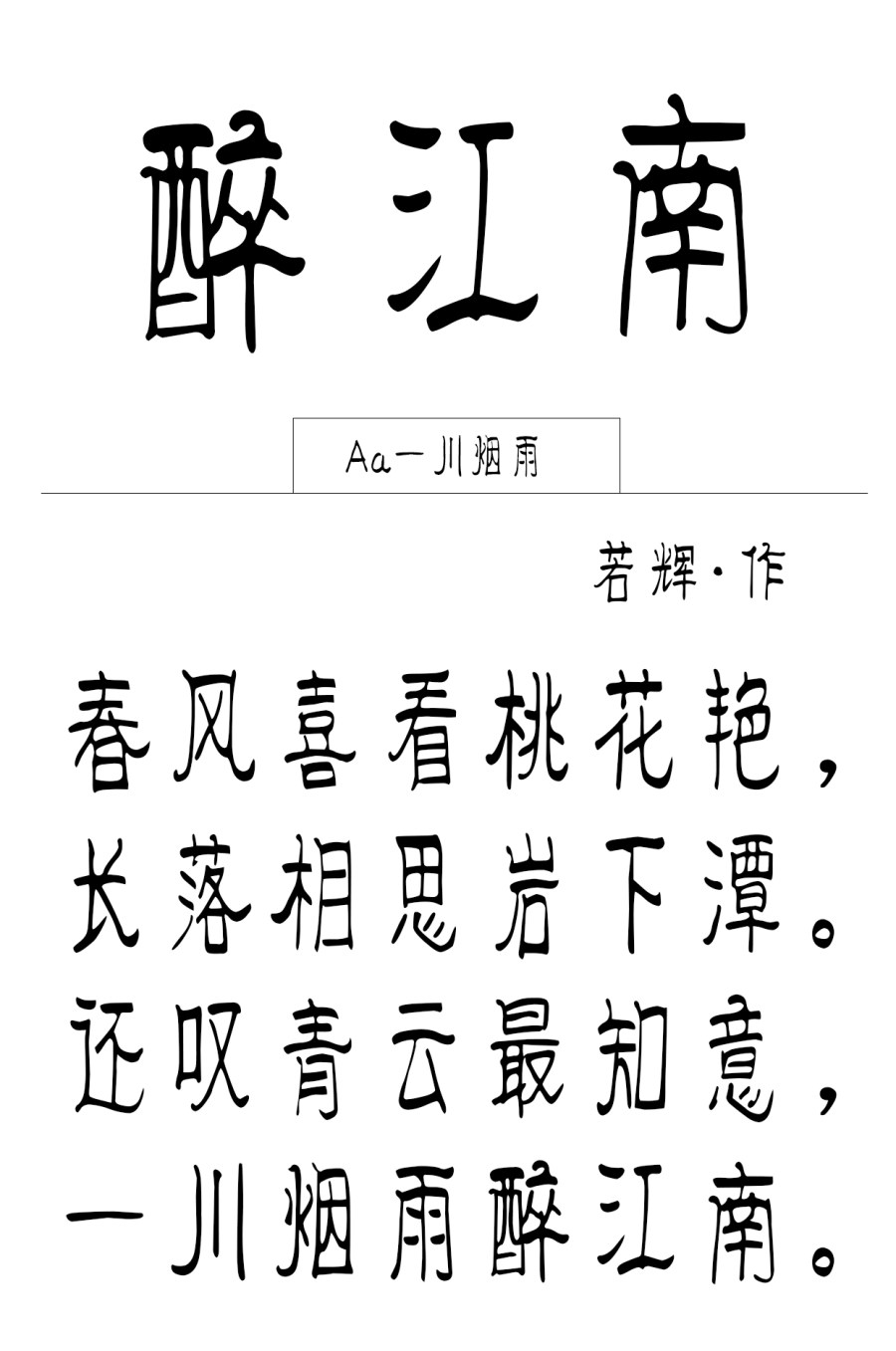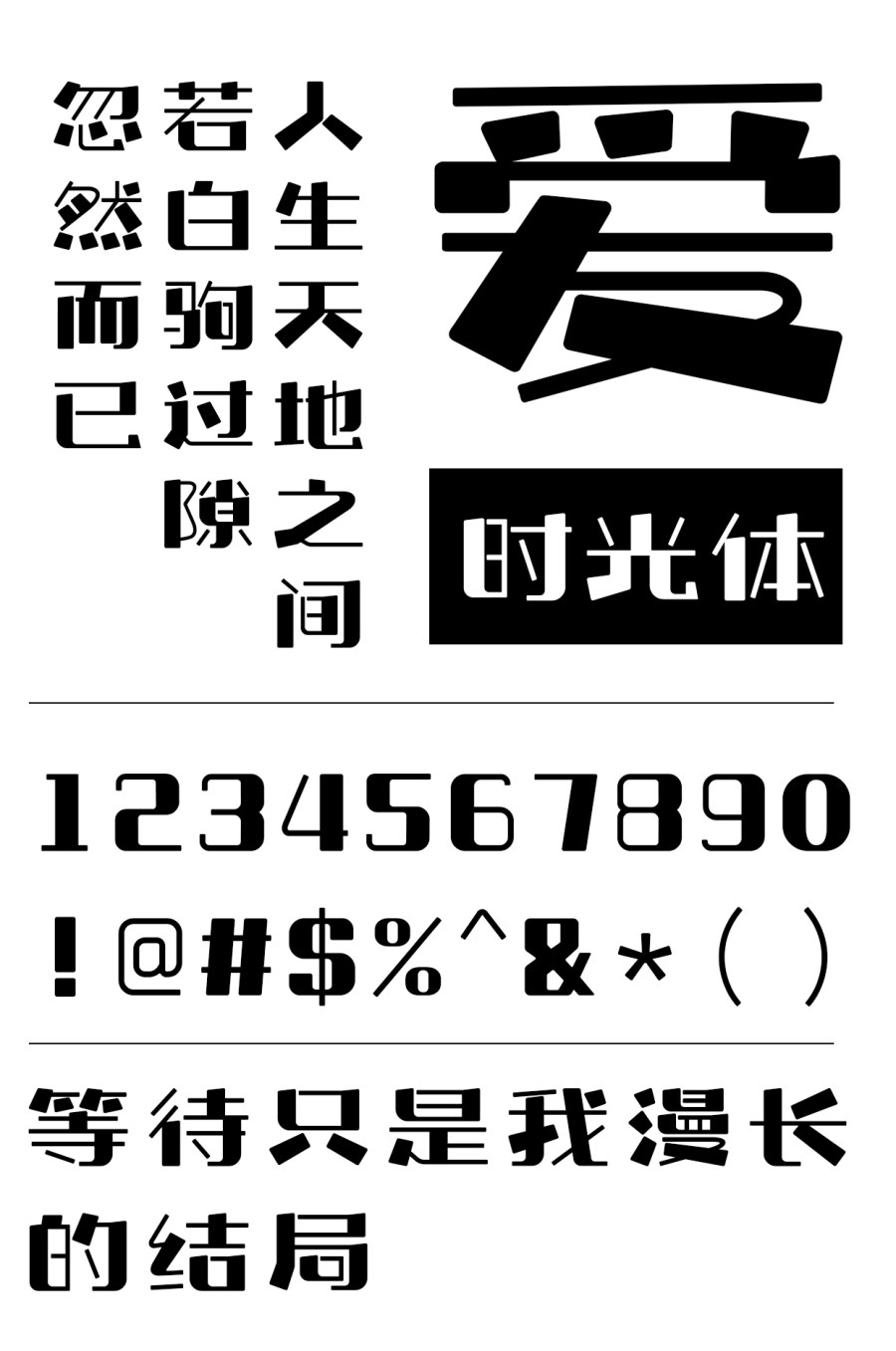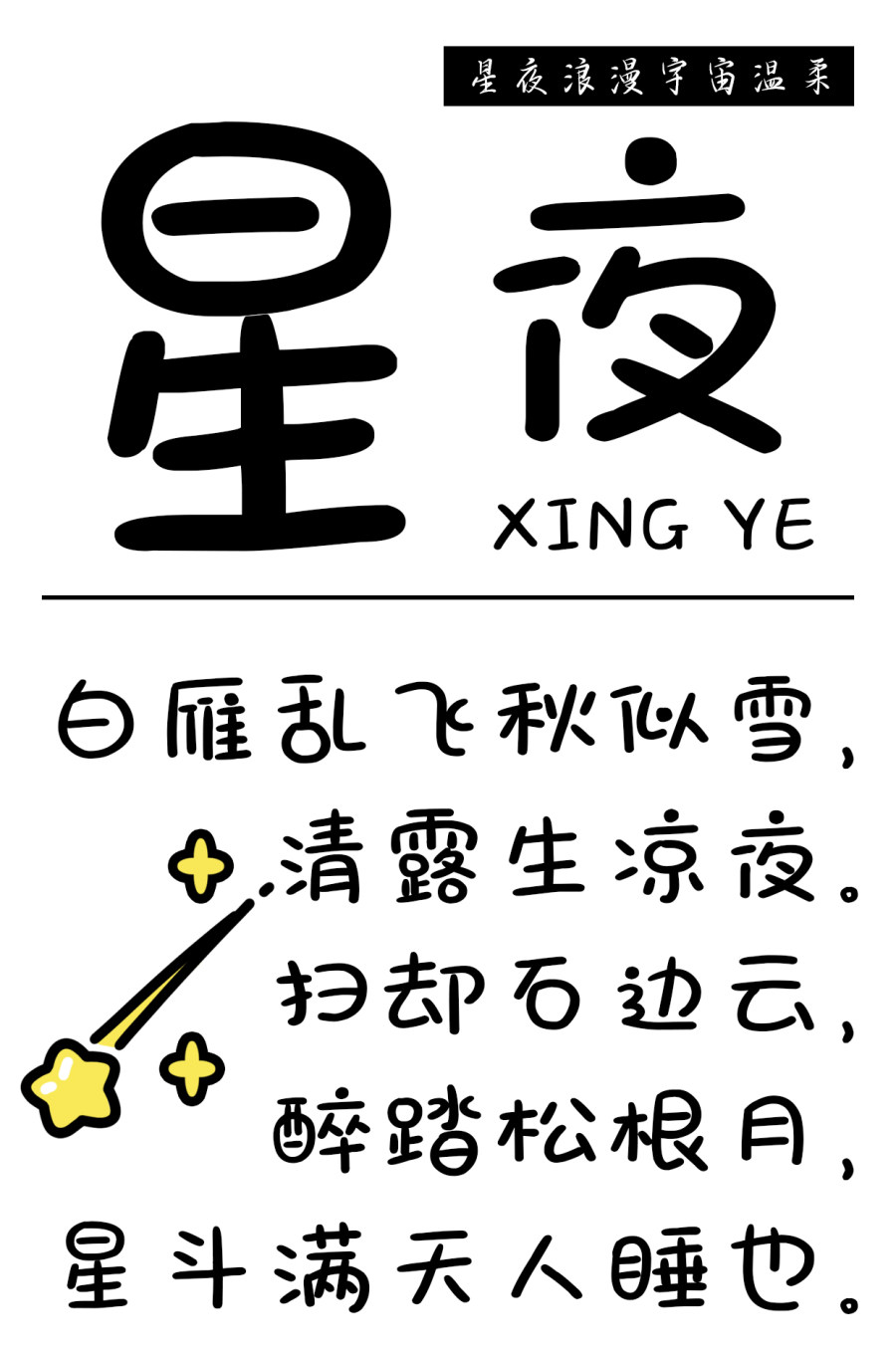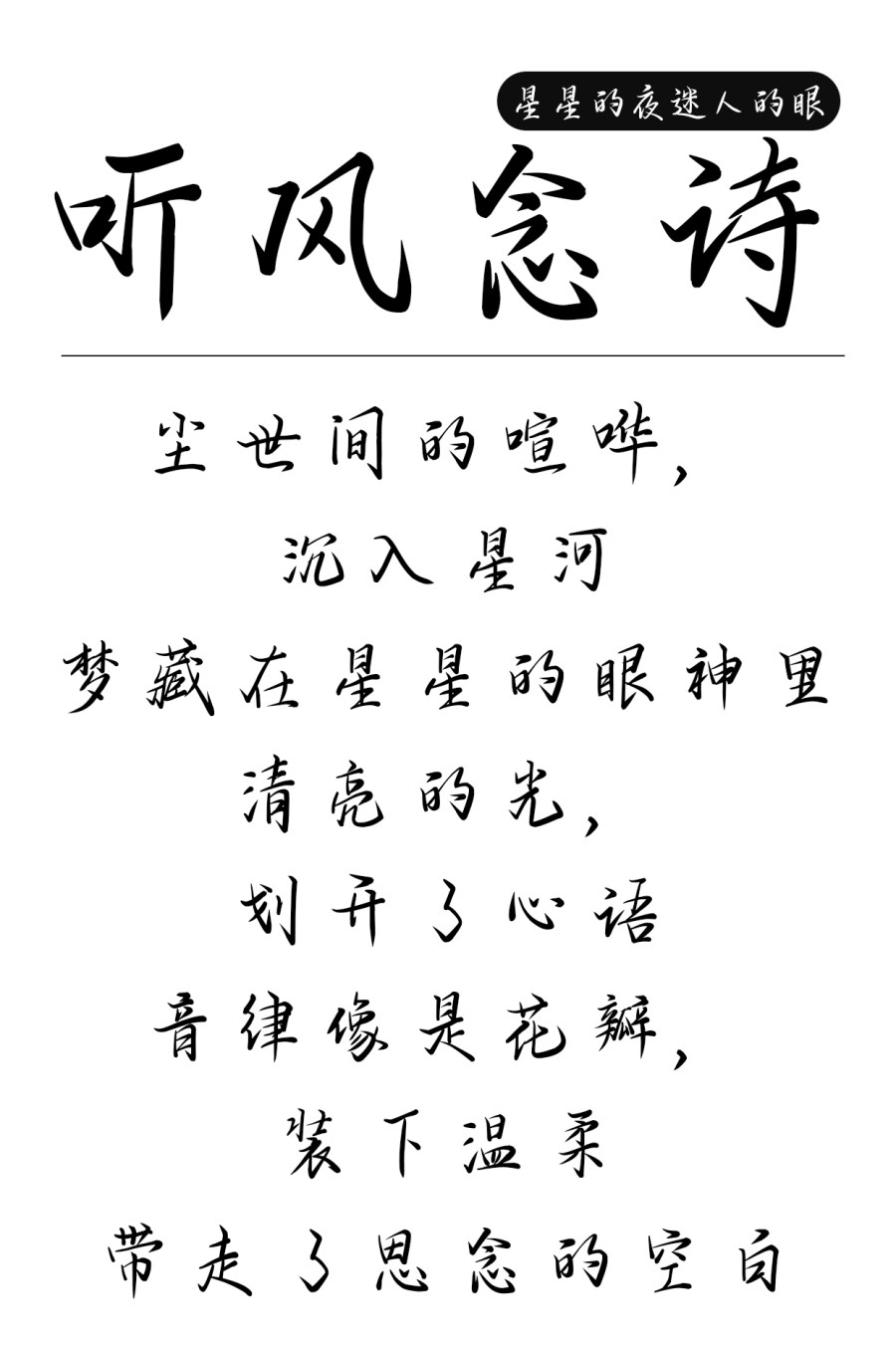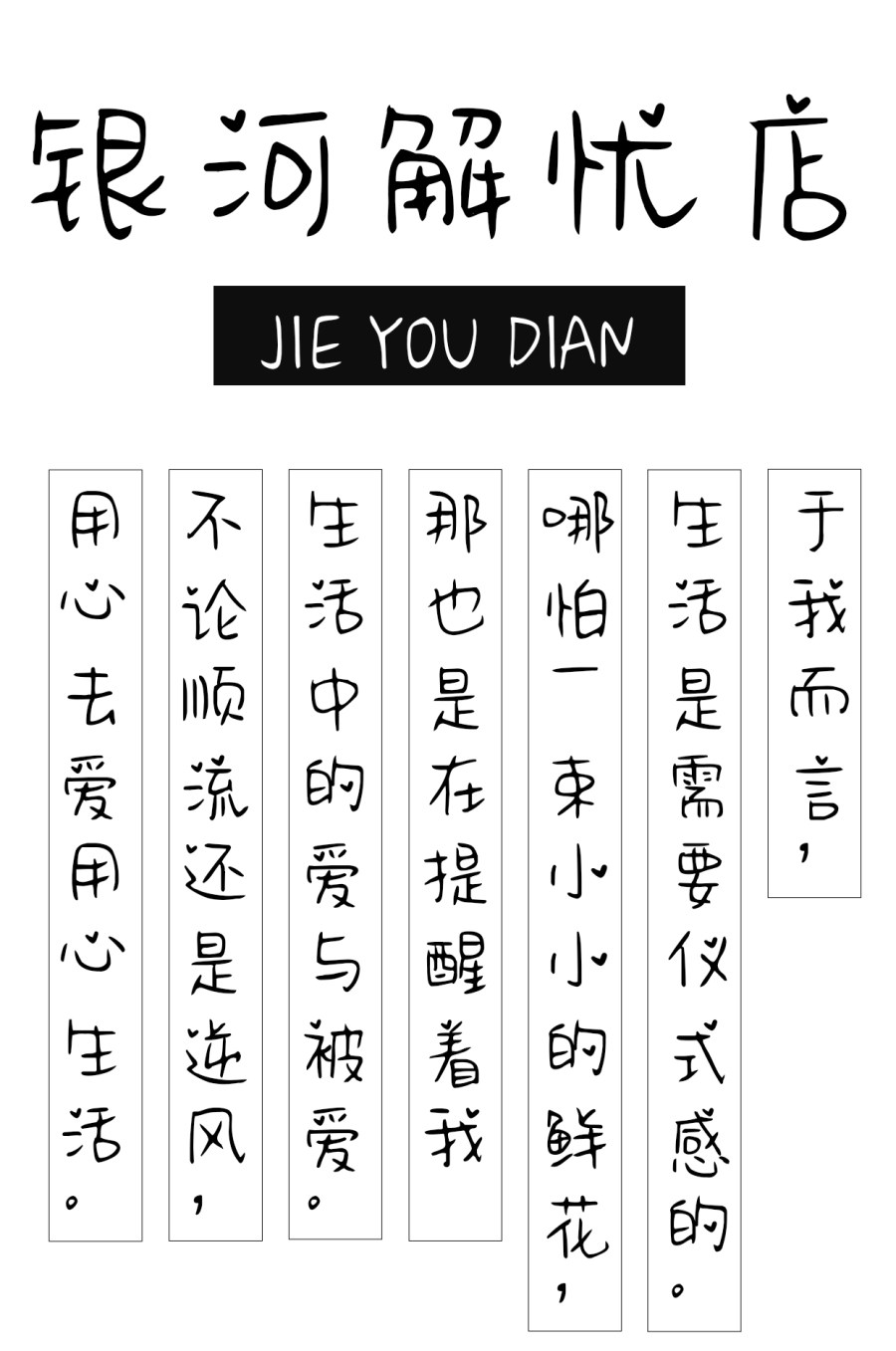
5月上线字体合集来啦
字体是设计中不可缺失的元素之一
越来越多的人在设计、排版和创意交流中使用到了各种各样的字体素材
今天给大家推荐的是5月份上线的新字
字体之美,尽在眼前
一起来看看吧
NO.1 上首御风书法体
上首御风书法体字体笔势潇洒飘逸灵动,随风飘荡,张力十足,动静结合,粗细对比强烈,更有视觉冲击,更加突出主题,让人印象深刻。
上首御风书法体
NO.2 上首蔷薇体
此套字形高瘦,采取蔷薇皮刺叶来作为设计原型,犹如蔷薇直立的形态,朵朵动人。文字新颖而又美丽的形态,令人如此着迷。
上首蔷薇体
NO.3 Aa一川烟雨
字形修长,笔画有横粗竖细的特点,结构稳定,内白清晰易于识别,是一款风格独特的手写装饰字体。多作为标题字体使用,适用于古风、人文等主题。
Aa一川烟雨
NO.4 上首时光体
整体字形方正,符合常规的字形,在字体设计时,对字体的笔划进行了设计,设计了粗细两种笔划,对笔划进行导圆,两种笔画共同构成单字,使得字的外部形态上具有了鲜明的风格。上首时光体
NO.5 上首东坡体
字体笔画横细竖粗,整体字型宽扁方正,沉稳肃穆,粗壮醒目。字体特点鲜明,艺术感十足。
上首东坡体
NO.6  上首胖虎体
字体笔画粗壮及多样,轮廓饱满。其内容比较丰富多样,整体风格比较稳重又带点胖胖的可爱,做到了风格、笔画、方向、空间的统一。
上首胖虎体
NO.7  Aa百物语
轻松随意,灵活多变的结构,强烈的粗细对比,为这款字赋予更多的活力,平直的笔画是这款字看起来更硬朗,粗细笔画交替运用是这款字更透气,字体中巧妙地运用了“点”的设计,为这款字赋予了更多的变化。Aa百物语
NO.8 星夜浪漫宇宙温柔
字体笔触柔和,线条纤细适中,字形变化不一,书写效果流畅,风格清新文艺。
星夜浪漫宇宙温柔
NO.9  星星的夜迷人的眼
字形古风书法墨韵形状,显得古典雅致,整套字体有如一气呵成,行笔迅捷华丽,其个性浪漫洒脱,适用于现代诗歌、短文的排版,以及文化、商业类品牌的广告语设计。
星星的夜迷人的眼
NO.10  Aa银河解忧店
卡通风格的手写体,字形方正、笔画简洁、书写灵活。部件大小错落、有节奏Aa银河解忧店